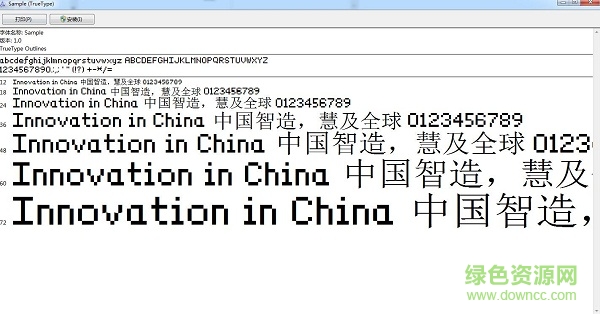
sample字體是一款像素風(fēng)的英文字體,字體特征鮮明,粗細(xì)一致,結(jié)構(gòu)勻稱,適用于像素游戲、電子屏幕、海報設(shè)計等各個領(lǐng)域,喜歡的朋友快來下載吧!
它的特征是在一定程度上擺脫了印刷字體的字形和筆劃的約束,根據(jù)品牌或企業(yè)經(jīng)營性質(zhì)的需要進行設(shè)計,達到加強文字的精神含義和富于感染力的目的,具有美觀大方,便于閱讀和識別,應(yīng)用范圍廣等優(yōu)點。